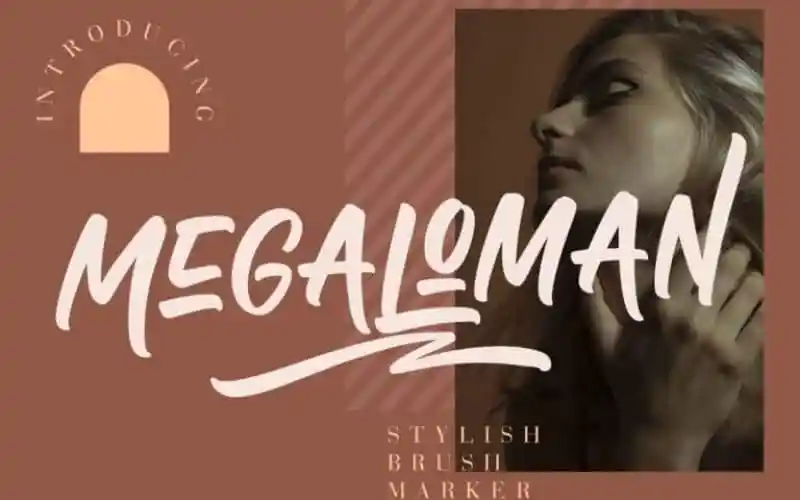
Megaloman Brush Font – Download Grátis
Megaloman Brush Font é uma fonte brush que traz estilo urbano e letras robustas num formato divertido e trendy. Ideal para designers que valorizam a criatividade e a personalização, essa fonte irá dar um toque único aos seus projetos digitais. Seja para criar logotipos inovadores, artigos de design gráfico ou qualquer outra aplicação visual, esta fonte promete transformar sua criação em uma peça icônica do mundo digital atual. Suas linhas finas e bold proporcionam um contraste interessante, enquanto o estilo retrô dos traços garante que cada trabalho final seja notável e imediatamente reconhecível. Engane-se apenas com a ideia de adicionar mais vida aos seus designs digitais com Megaloman Brush Font.